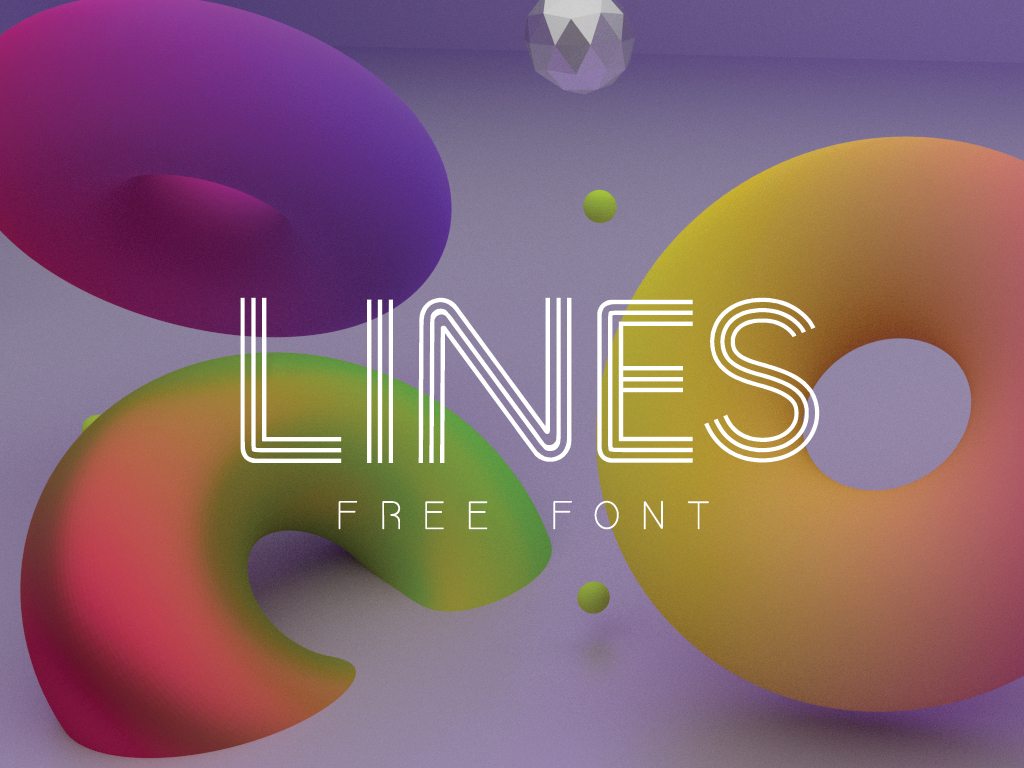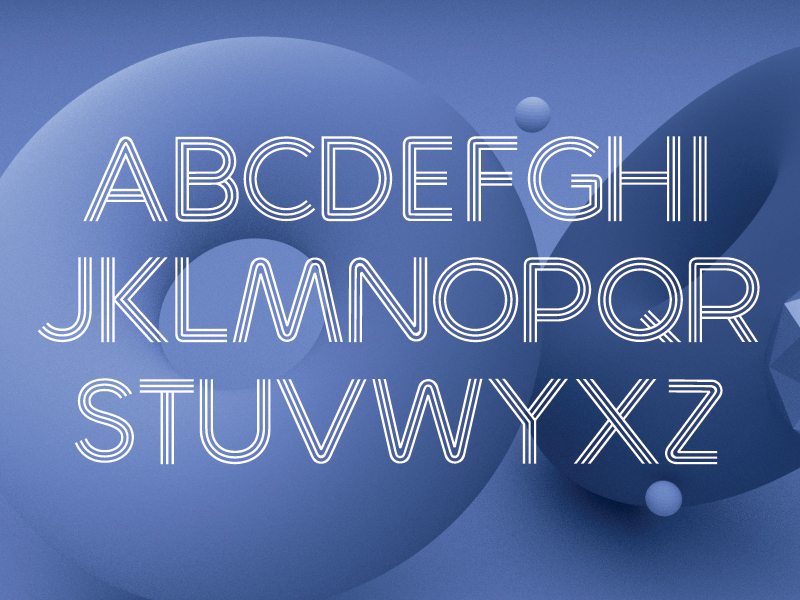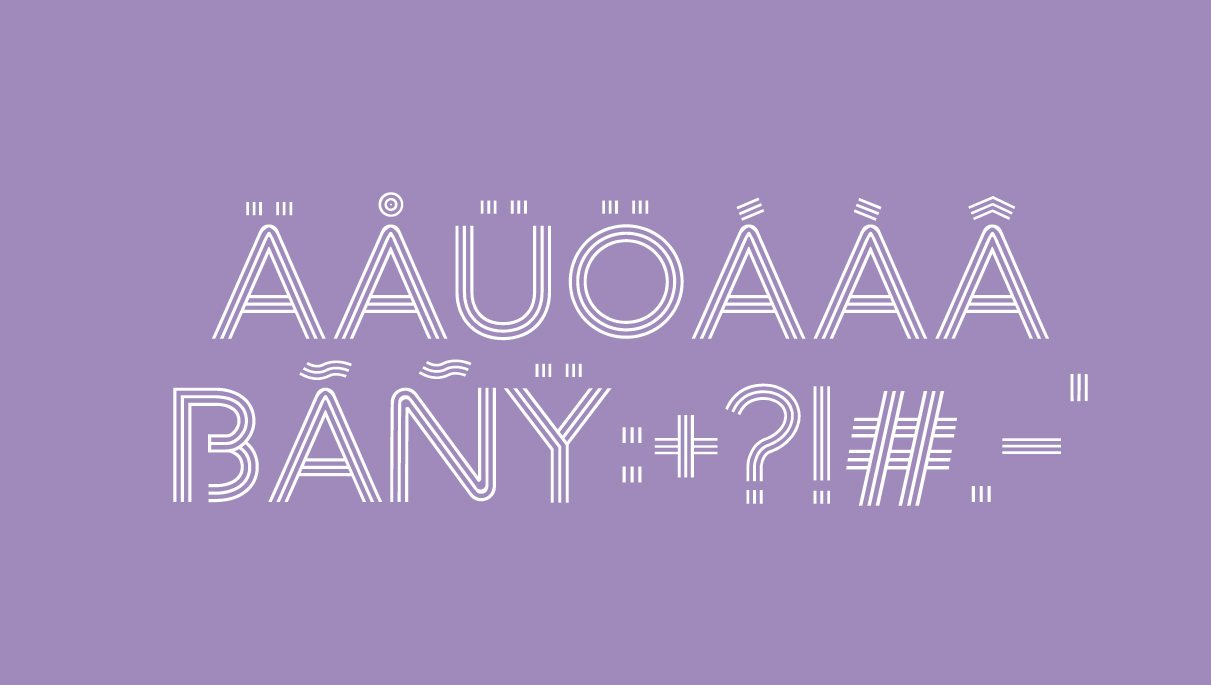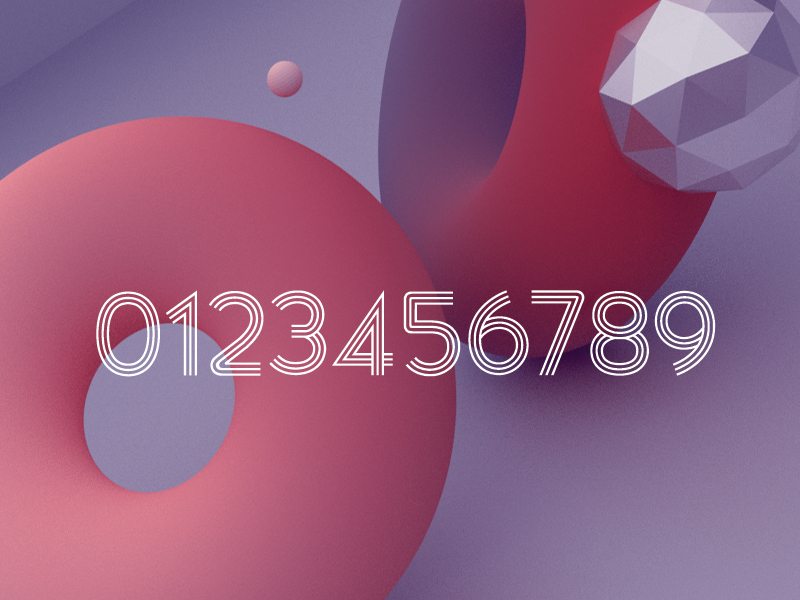
Font del Giorno: Lines
Il font che vi presentiamo oggi é: LINES
Lines è il nuovo font di FGD realizzato da Marcelo Reis Melo.
Un font moderno con caratteri adatti per la lingua  inglese, svedese e tedesco. Minimalista e pulito, ma che con le sue diverse linee lo rende accattivante e fresco,mi  ricorda la scritta Arcade Flin’s del film Tron per certi versi, a voi no?